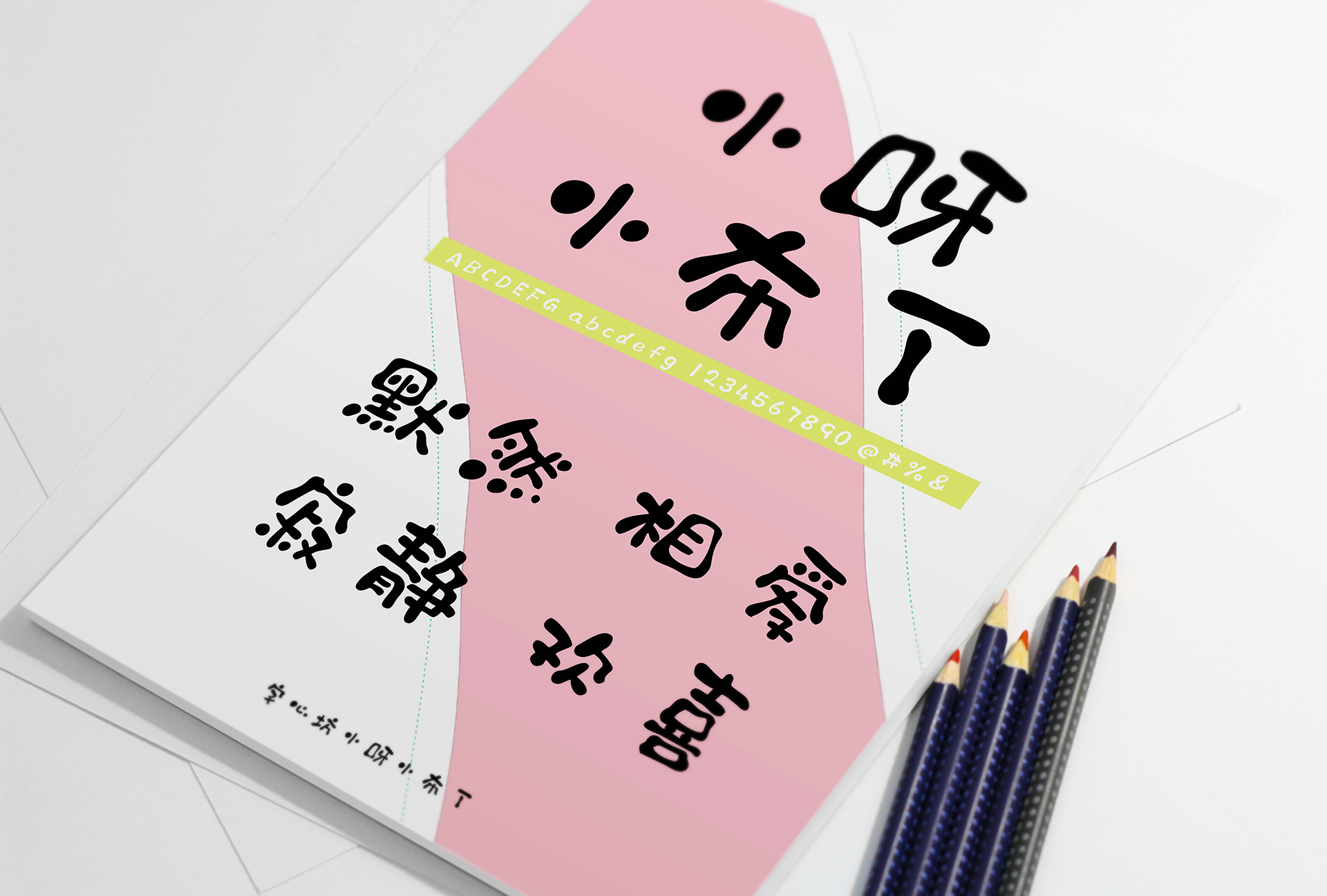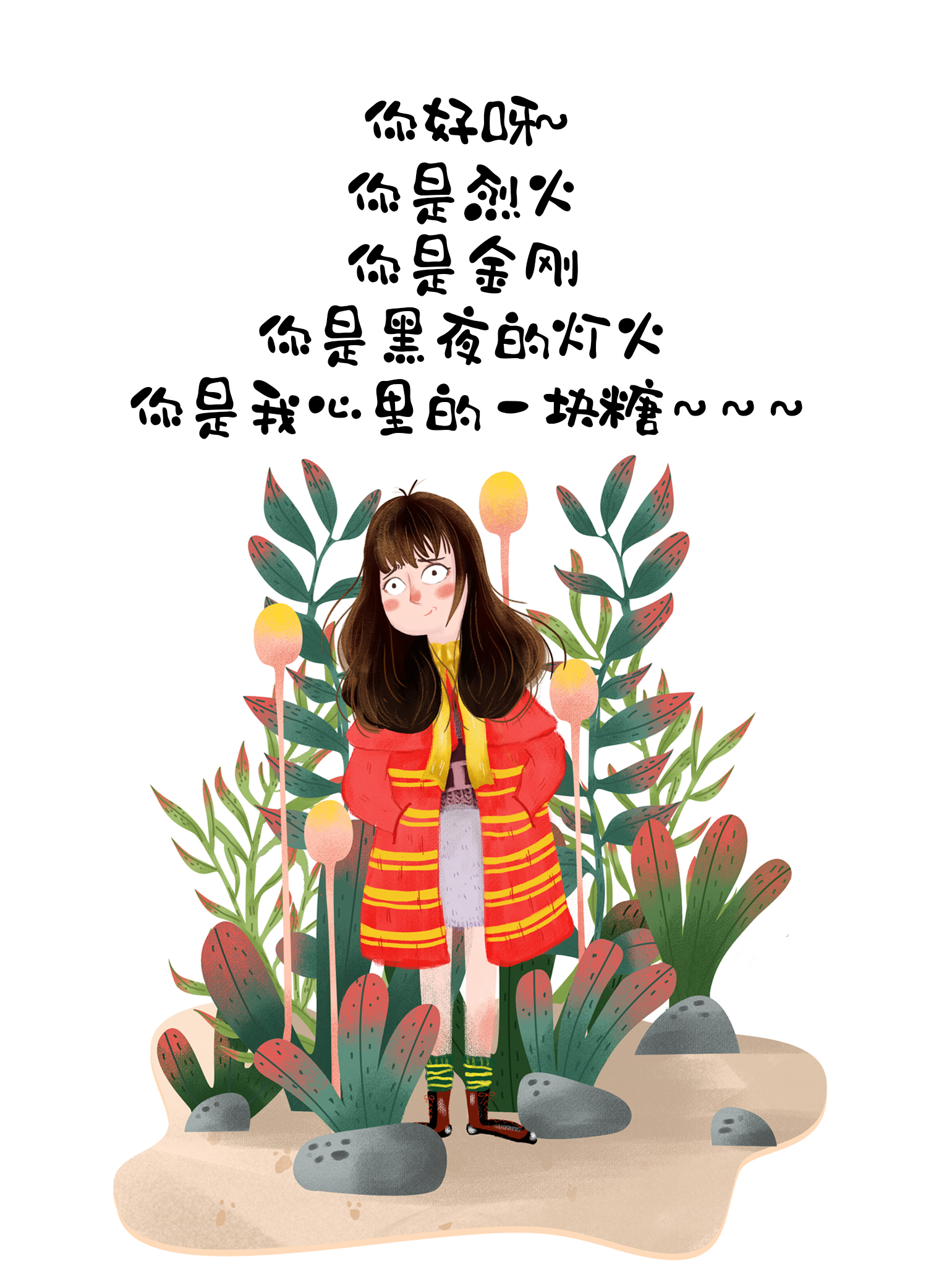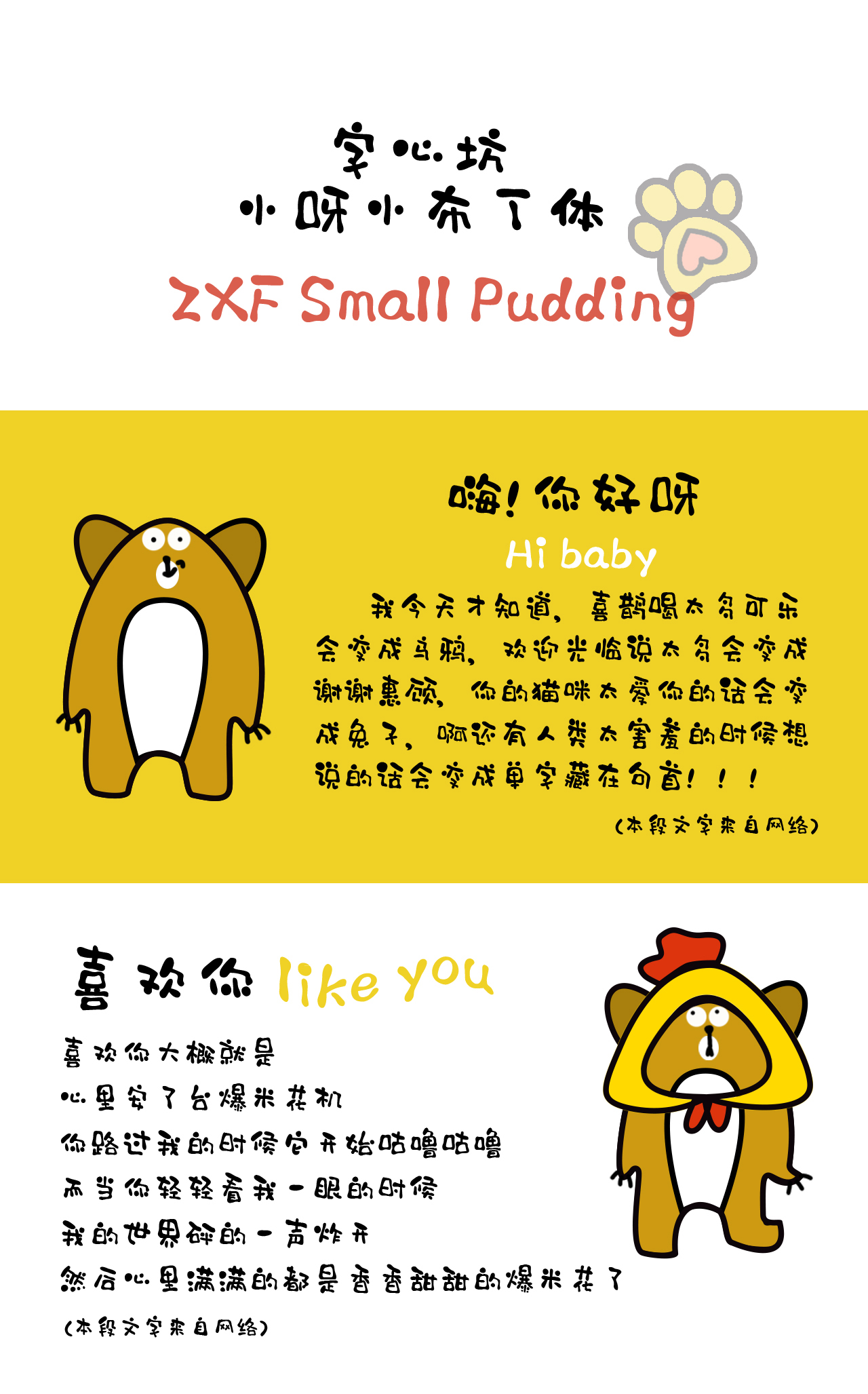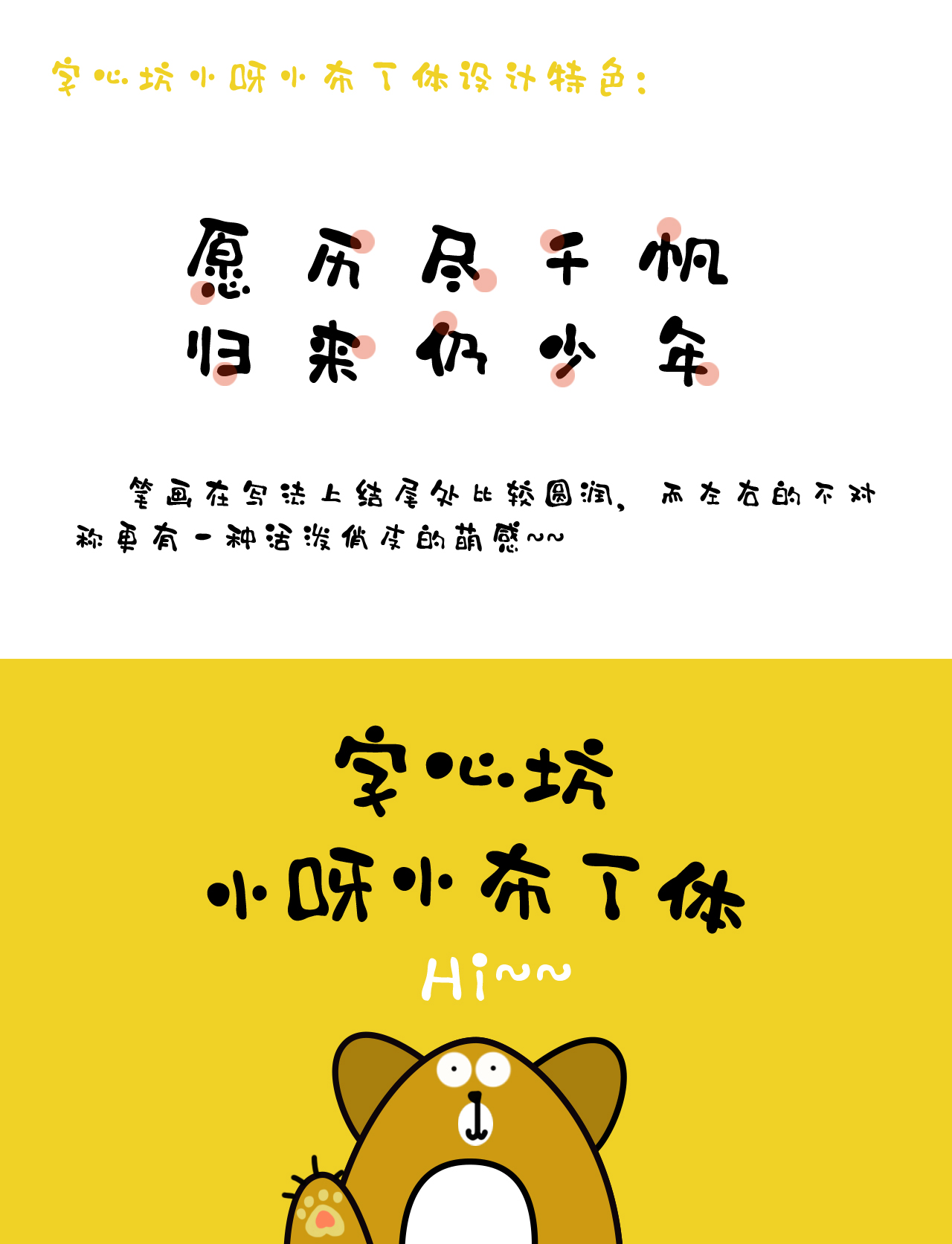
字心坊小呀小布丁
该字体由一位古灵精怪的魔法少女创作而成。前期书写过程能充分的反映出创作者心灵对于美好心境的诠释。后经电脑设计软件进行修正、编辑,最后做成计算机字库。字体风格新颖、可爱、个性、小清新、时尚、有趣,适用于标志、导视、书籍、游戏、动漫、影视、屏显等方面。
字体风格:文艺 / 小清新 / 卡通 /可爱/ 时尚
推荐场景: 标志 / 导视 / 书籍 / 游戏 / 动漫 / 影视 / 屏显